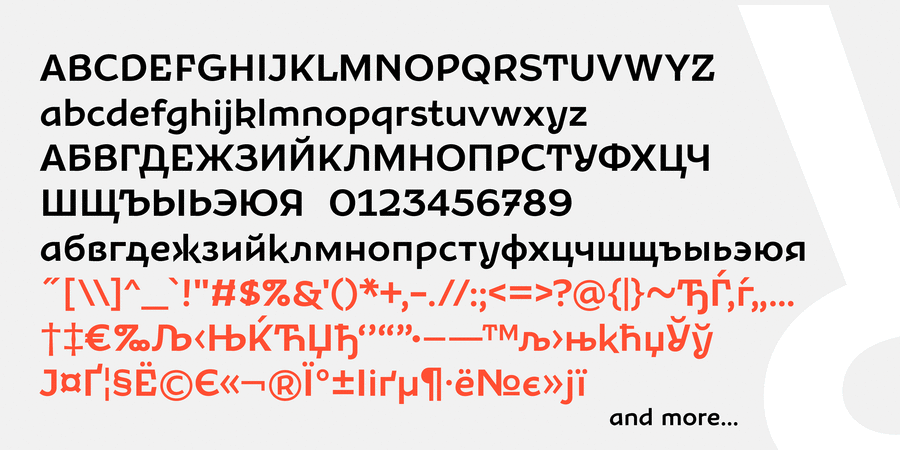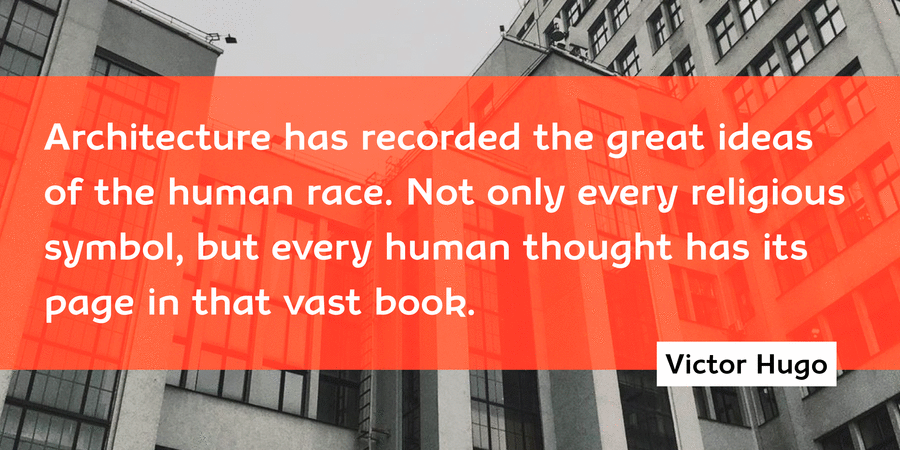
Aleksa – шрифтове сімейство, що поєднує в собі стриманість гуманістичного гротеску та грайливість традиційних українських форм початку 20 століття. Такий контраст робить шрифт незвичним, динамічним і приємним на вигляд. Гарнітура складається з 9 насиченостей (від супертонкої до ультражирної), а також має курсиви. Це універсальний гротеск, що чудово працює в багатьох видах дизайну, від логотипів до набірних текстів. Сімейство розробили Кирило Ткачов і Марчела Можина у 2020 році.
Асоціації з сімейством шрифтів AleksaОсобистість і характер гарнітури:
чіткий, делікатний, легкий, свіжий, тонкий, якісний, міський, крихкий, дротяний, самобутній, цікавий, оригінальний, характерний, розв'язний, живий, етнічний, вольний, колоритний, артистичний, художній, динамічний, вільний, гуманітарний, ритмічний, культурний, творчий, незвичайний, твердий, дотепний, акуратний, доброзичливий, відкритий, довірчий, виразний, племінний, ввічливий, здоровий, бадьорий, приємний, гнучкий, гладенький, комфортний, активний, яскравий, сміливий, щедрий, помітний, рясний, насичений, теплий, серйозний, впевнений, стійкий, переконливий, смачний, дерев'яний, значний, сильний, важкий, важливий, грубий, мотивуючий, чорний
мода, Місто, дієта, дизайн, історія, культура, графіка, ілюстрація, архітектура, одяг, реклама, магазин, театр, фольклор, музика, література, танець, торгівля, реконструкція, ремесло, відпочинок, туризм, табір, гумор, банкнота, йога, пам'ятник, меморіал, їжа, закуска, монета, скульптура, дерево, гроші Гарнітура має ознаки стилів: